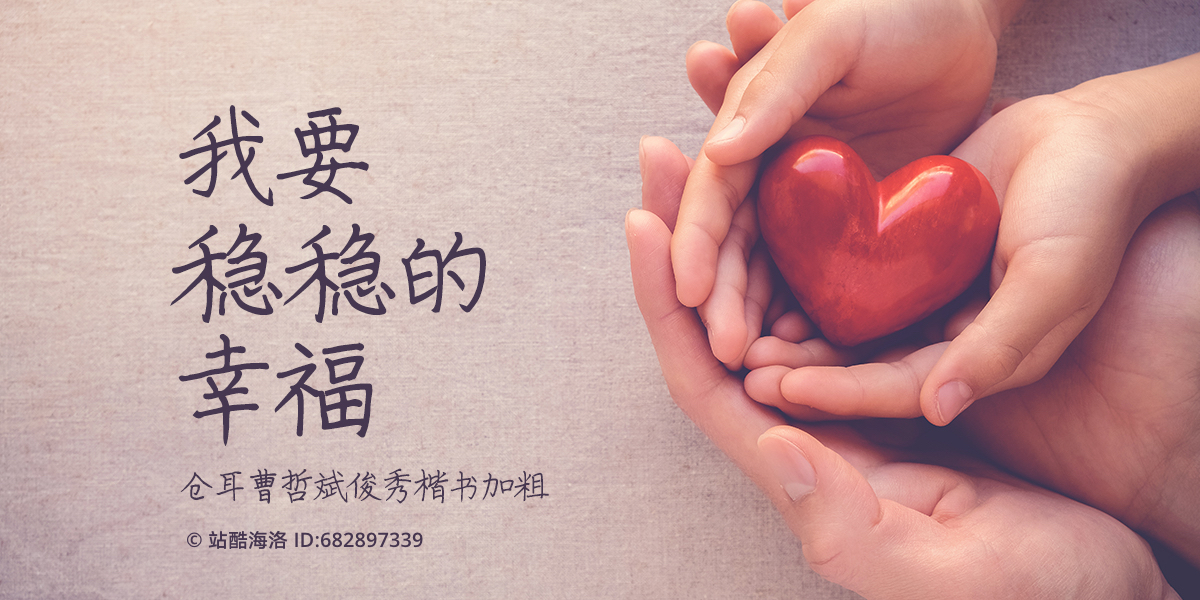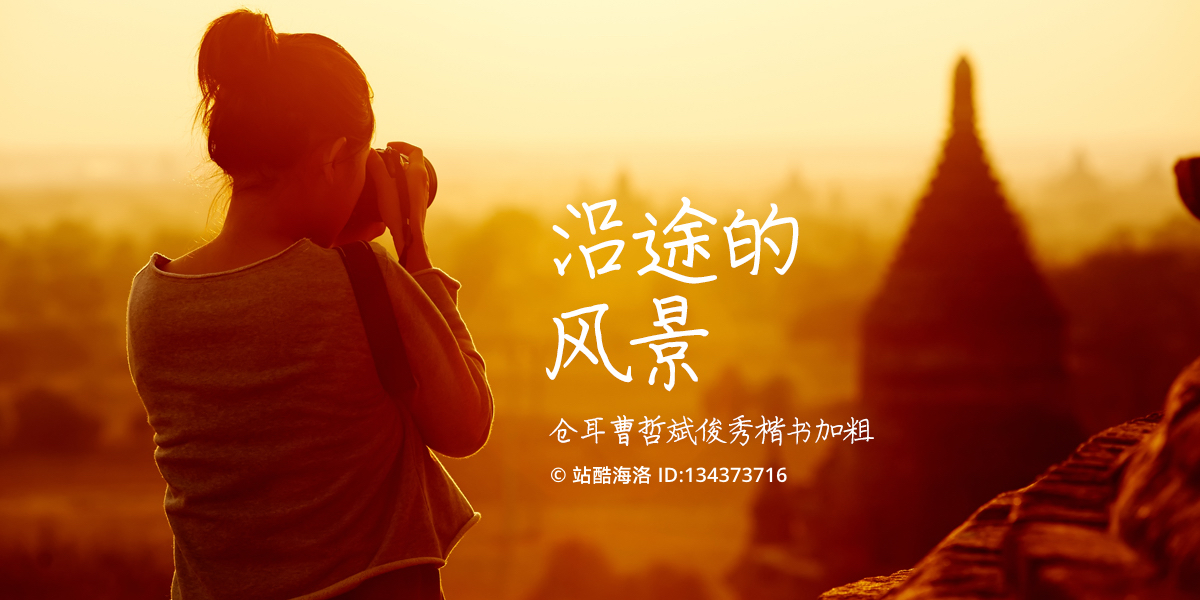
仓耳曹哲斌俊秀楷书加粗
仓耳曹哲斌俊秀楷书加粗,这款手写字体借鉴楷体的字形结构,中宫较为紧凑,字形高挑,端庄大方、运笔自然流畅,将笔画加粗,结构清晰易识读,取匀衡瘦硬,追魏碑斩钉截铁之势,点画爽利挺秀,骨力遒劲,结构严紧。 这款字体借鉴传统楷体的字形风格,但又有别于传统楷体。特意加粗的笔画增加了字体的识读性。为了使字体更加秀丽,将字体的中宫收紧,字形拉长,使用更加舒适。
仓耳曹哲斌俊秀楷书加粗字体介绍